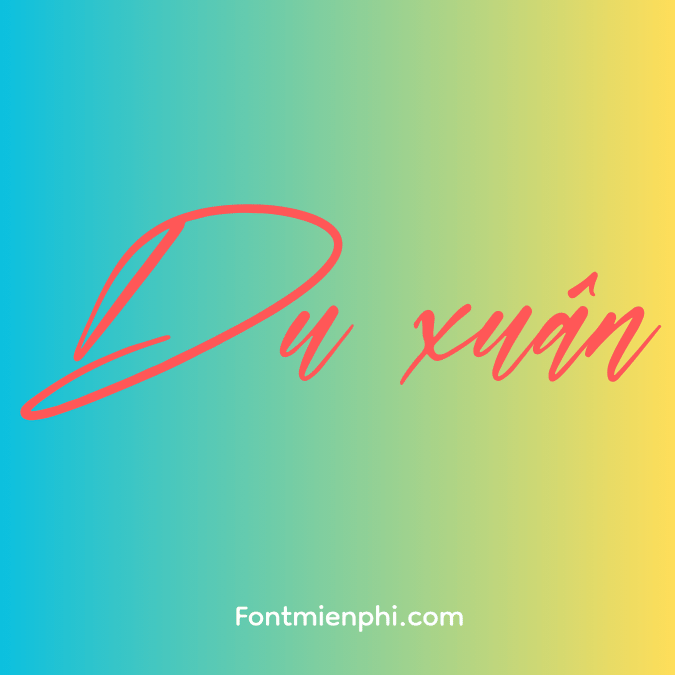
Font Việt hóa 1FTV VIP Archattson Hollmytro
Font Việt hóa 1FTV VIP Archattson Hollmytro là một kiểu chữ đặc biệt được thiết kế để phục vụ nhu cầu sử dụng tiếng Việt một cách hiệu quả và thẩm mỹ. Với sự phát triển của công nghệ và thiết kế đồ họa, việc lựa chọn font chữ phù hợp là rất quan trọng, không chỉ giúp truyền tải thông điệp mà còn tạo ấn tượng mạnh mẽ cho người đọc.
Tính năng nổi bật của Font Việt hóa 1FTV VIP Archattson Hollmytro:
1. Thiết kế hiện đại và tinh tế: Font này có kiểu dáng hiện đại, giúp nó dễ dàng hòa hợp với nhiều phong cách thiết kế khác nhau, từ cổ điển đến đương đại. Sự kết hợp giữa các đường nét mềm mại và góc cạnh tạo nên một diện mạo độc đáo.
2. Hỗ trợ ngôn ngữ tiếng Việt: Một trong những ưu điểm lớn nhất của font này là khả năng hỗ trợ đầy đủ các ký tự tiếng Việt, bao gồm cả các dấu câu và ký tự đặc trưng. Điều này giúp người dùng dễ dàng tạo ra các tài liệu, bài viết hay sản phẩm đồ họa mà không gặp phải vấn đề về hiển thị chữ.
3. Độ rõ nét và dễ đọc: Font Việt hóa 1FTV VIP Archattson Hollmytro được thiết kế với độ rõ nét cao, đảm bảo rằng các ký tự luôn sắc nét, dễ đọc ở nhiều kích thước khác nhau. Điều này rất quan trọng trong việc tạo ra nội dung dễ tiếp cận với người dùng.
4. Tính linh hoạt trong ứng dụng: Font này có thể được sử dụng trong nhiều lĩnh vực khác nhau như thiết kế đồ họa, quảng cáo, logo, hoặc các sản phẩm in ấn. Sự đa dạng này giúp người dùng có thể tự do sáng tạo mà không bị giới hạn.
5. Dễ dàng kết hợp với các kiểu chữ khác: Font 1FTV VIP Archattson Hollmytro có thể phối hợp tốt với nhiều kiểu chữ khác nhau, tạo ra sự đa dạng và phong phú trong thiết kế.
Với những đặc điểm nổi bật trên, Font Việt hóa 1FTV VIP Archattson Hollmytro chắc chắn sẽ là một lựa chọn tuyệt vời cho những ai đang tìm kiếm một kiểu chữ đáp ứng đầy đủ yêu cầu về thẩm mỹ và chức năng trong việc sử dụng tiếng Việt. Hãy thử ngay hôm nay để nâng cao chất lượng sản phẩm thiết kế của bạn!